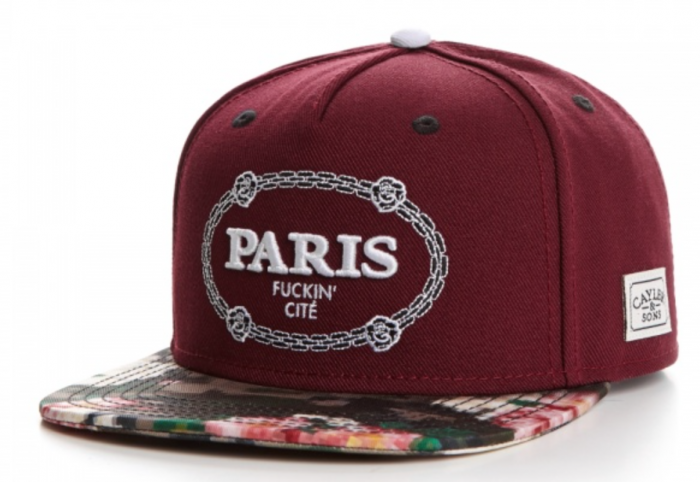
ich suche die Schrift des Schriftzuges auf dem folgenden Bild
da muss man teilweise raten. Durch das Sticken verändert sich die Vorlage doch extrem und bei Schriften ist das dann sehr entstellend. Schon daher kann man die Schriften nicht genau identifizieren. Hier mal meine Rateversuche:
1) "PARIS" ist irgend eine misshandelte Garamond? ITC-Garamond eingefettet und ggf. etwas in die breite gezogen?
2) "FUCKIN' CITÉ" da drunter könnte/sollte es eine Futura (Medium?) sein. Diese sollte in etwa dieses Schriftbild geben.